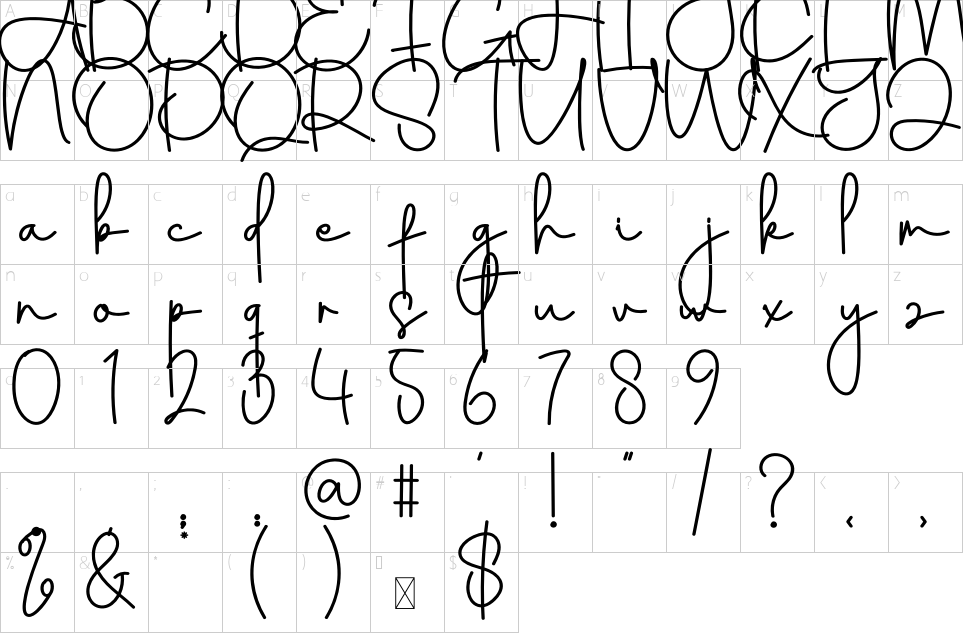
Amsterdam Christmas Font – Download Grátis
Descubra a magia do Natal com a Amsterdam Christmas Font, uma opção de fontes grátis perfeita para o ambiente natalino. Desenhada por scratchones, esta fonte traz um toque especial ao seu design gráfico natalino. Com uma elegância e um toque delicado que remetem à atmosfera encantada do Natal, a Amsterdam Christmas Font é perfeita para decorar cartazes, flyers e até mesmo cartões de Natal. Se você procura uma fonte de qualidade para decorar seu site ou aplicativo durante o Natal, esta é a escolha certa. Com um design minimalista e uma versatilidade única, a Amsterdam Christmas Font torna sua mensagem de Natal mais especial. Para baixar esta fonte, basta visitar o site e conferir o download gratuito disponível para Windows e Mac. Recomendamos experimentar, especialmente se você está buscando uma fonte de alta qualidade para seus projetos de Natal.